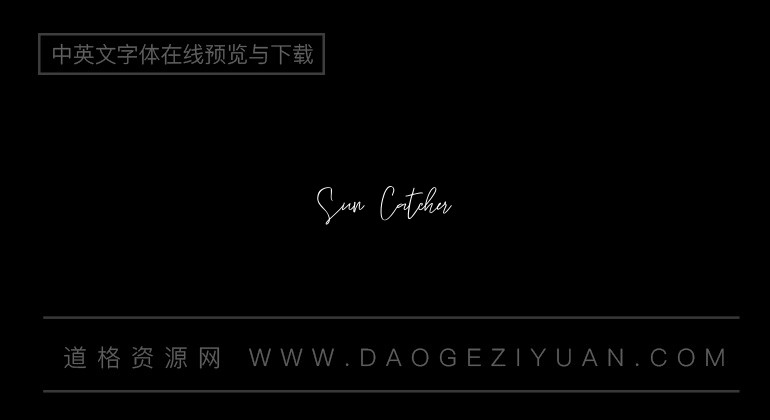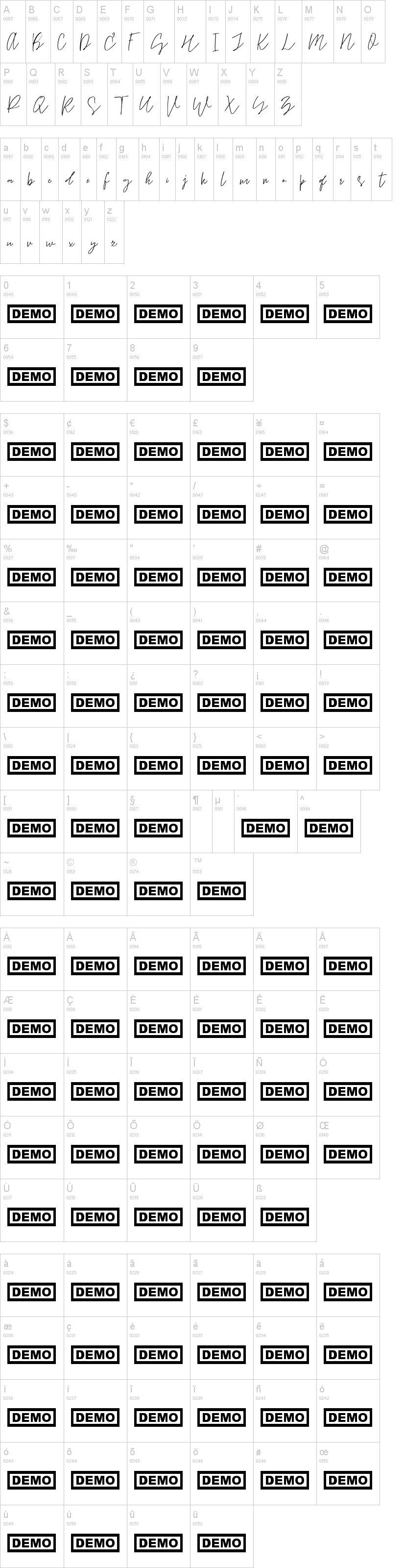
Sun Catcher
Sun Catcher 是一种非常漂亮的手写体字体,由设计师Marek Tracz创建。它的特点是具有光泽感和流动性,仿佛能够捕捉到阳光的微光,因此被称为Sun Catcher(太阳捕手)。该字体适用于多种设计场合,如标题、海报、卡片等。它的线条流畅,笔画有很好的变化,可以在设计中增加艺术气息和温暖感。此外,Sun Catcher 字体还带有一些装饰性的元素,例如点、线和花瓣,可以用于装饰字母。总之,Sun Catcher 是一款非常优美的字体,适用于多种设计和排版需求。
Sun Catcher是一款非常不错的手写艺术字体,具有很好的视觉感,适合于文化类的宣传设计、商业类品牌的广告和产品包装设计以及个性化文字排版等较多场景。
Sun Catcher字符映射图